今回は、どこか不穏で、常識からズレたような「奇怪な雰囲気」のある日本語フリーフォントをご紹介します。
文字なのに“何かがおかしい”そんな違和感を抱かせるフォントは、都市伝説や怪談、オカルト、アングラ系の表現にぴったり。不安定な形状、ゆがみや崩れを感じるライン、歪んだバランスなどが相まって、見る者の心にゾワっとさせることもできるフォントばかりです。
今回は、得体の知れない空気感をまとう“奇妙でクセのある”日本語フリーフォントをピックアップしました。怪異・都市伝説・退廃的な物語の演出など、普通では物足りないシーンにぜひ活用してみてください。
不気味・歪み・不穏さ。奇怪な日本語フリーフォントまとめ
以下のフォントのような、「いつも見ている文字とはちょっと違う?」雰囲気をもつ奇怪なフリーフォントをご紹介します。
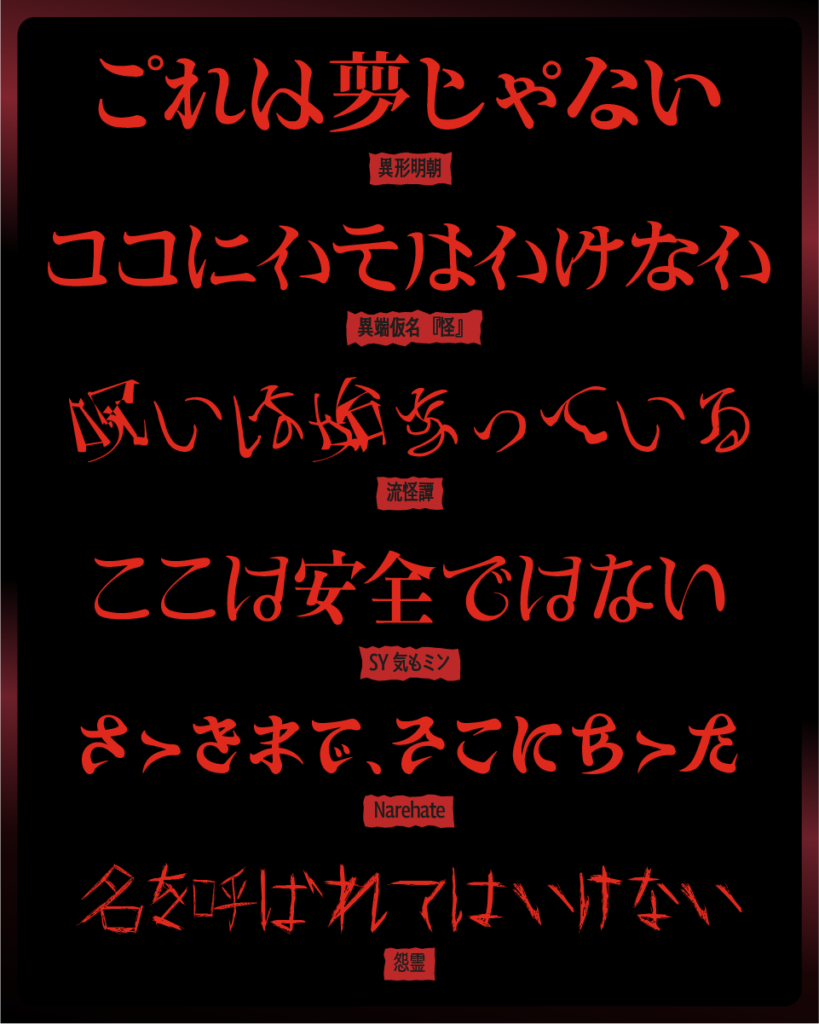
異形明朝
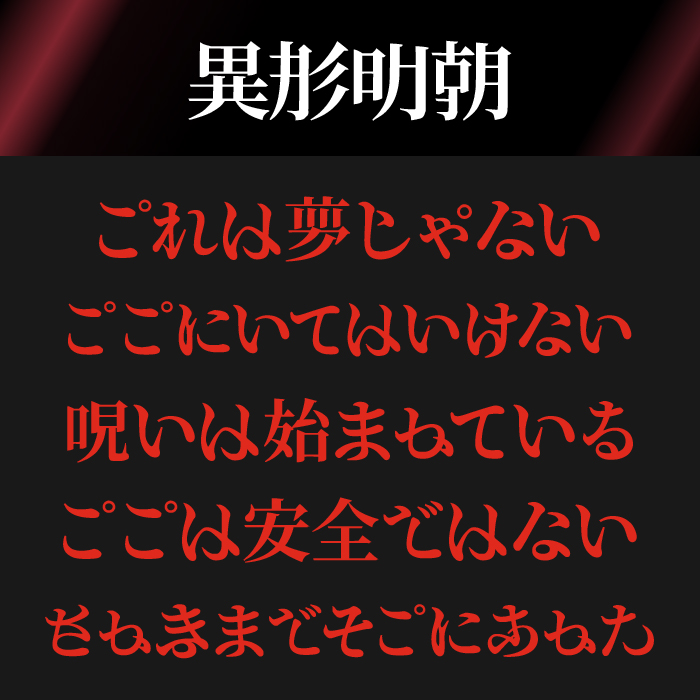
異形明朝は、通常の明朝体のシルエット違い生成AIでチューニングして作られた、異常性と不安感をにじませたフォントです。一見すると美しいが、長く見ているとゾクっとくる異質さを孕んでいます。
怪異の中にある静けさ、不可解な事件、正体不明の存在…といったモチーフとの親和性が高く、ホラー明朝の入り口としても使いやすいフォントです。
流怪譚
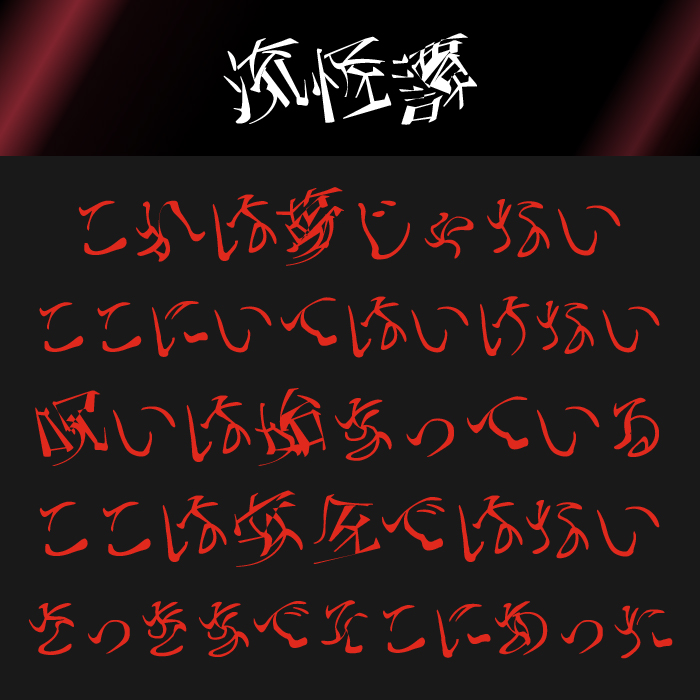
流怨譚は、ぐにゃ〜っと回転しているようなカーブが不気味なフォントです。優雅さを装いながら、明らかにどこかおかしいという違和感があります。
物語性のある怪奇演出、妖しさを含んだ伝奇もの、あるいは「何かが始まりそう」な序章に向いています。視線を引きつける妖艶さと不穏さを併せ持つ稀有なデザインです。
怨霊フォント
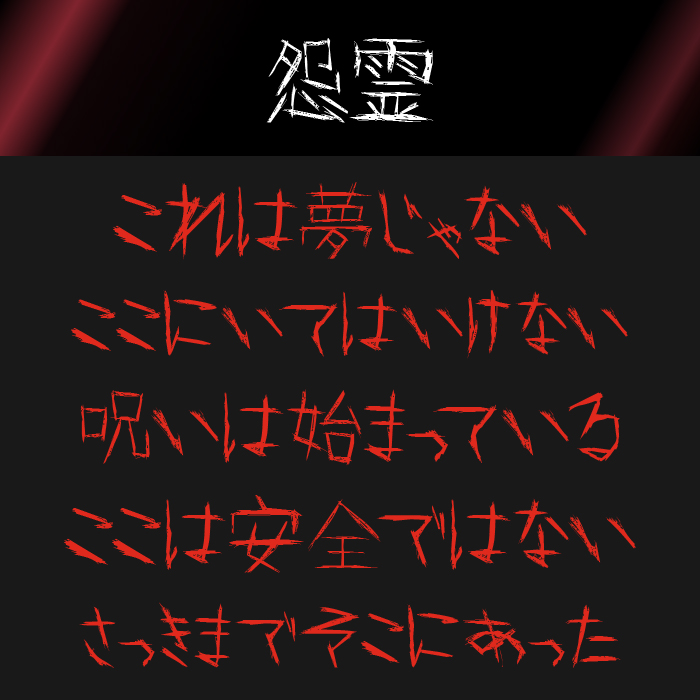
怨霊フォントは、爪で引っ掻いたような筆跡に鋭利さと怒りを宿したような、刺々しい手書き風のデザインです。文字のひとつひとつが叫びのように見え、見ただけで「呪われそう」な緊迫感があります。
恐怖や怨念といったテーマに直結しており、心霊映像やホラー演出のタイトル・字幕などに最適です。過激で破滅的な印象を与えたい場面にぴったりのフォントです。
白舟篆古印
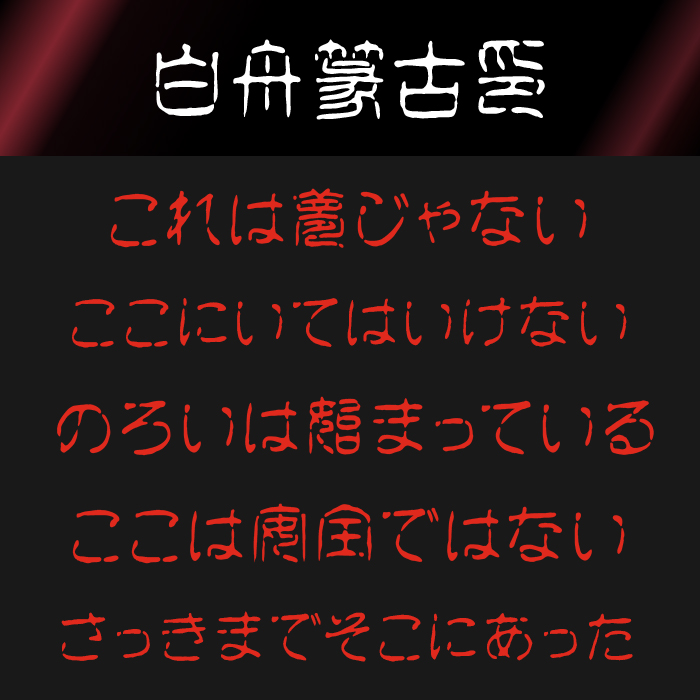
古印体をモチーフとした掠れた筆致が特徴的なおどろおどろしさのある奇怪フォントです。細身ながら芯のある線が、消えかけた怨念や記憶を連想させます。
呪いや怨霊、廃墟、禁忌といったテーマの演出に非常に強く、画面に文字があるだけで物語の温度を一気に冷やすそんなフォントです。
SY気もミン
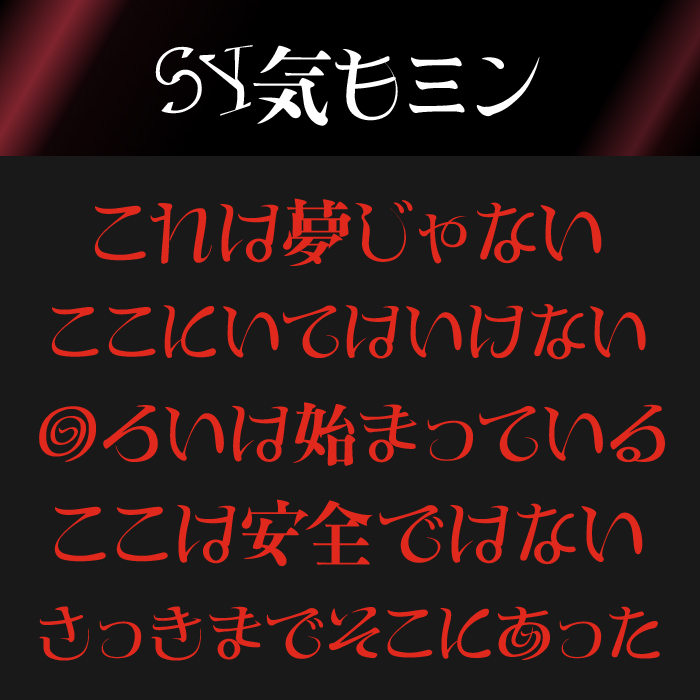
SY気もミンは、ぐにゃとした筆終わりがとっても特徴的で、部分的に奇怪な装飾が施された異形フォントです。曲線と突起が混在し、柔らかさの中に危うさを感じさせます。
いわく付きの手紙、呪文、謎の記号…といった「読めるけど怖い」文字演出にぴったり。
異端仮名『怪』
異端仮名『怪』フォントは、ひらがなとカタカナの融合した異形の文字にゾクゾクとしてしまうユニークなデザインフォントです。
ひらがなとカタカナが組み合わさって作れらていることで「これはなんだろう?」と一見ギョッとしてしまう形ながら、よく見ると読めてしまう不思議なフォントです。
Narehate(なれはて)
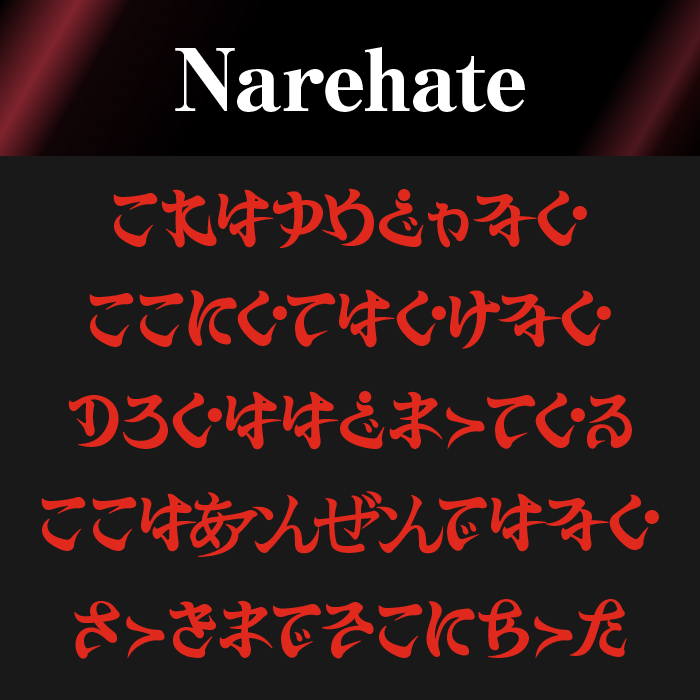
Narehate(なれはて)フォントは、ひらがなの成れの果てのように変形させたデザインフォントです。滑らかながらもどこか常軌を逸したフォルムが、言い知れぬ不安を誘います。
ボトムズ
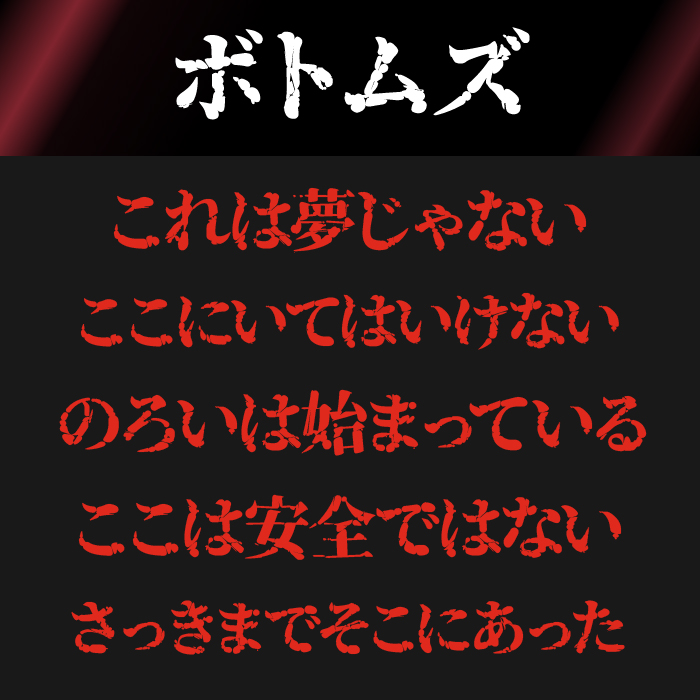
ボトムズフォントは、源ノ明朝をベースとして、沼の底のようなテクスチャを加えて制作されたデザインフォントです。沼底のような奇怪的な強さのあるフォントです。
吐き溜
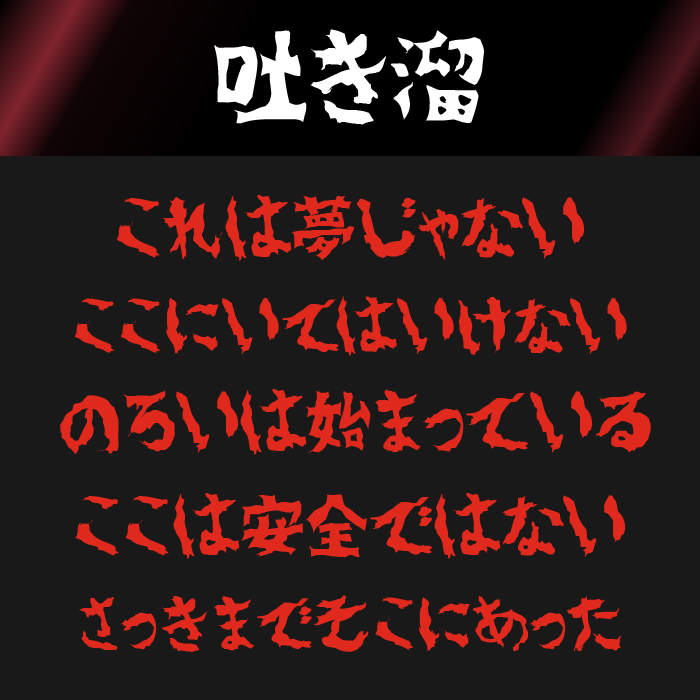
吐き溜フォントは、血が滲んだような鋭利なアウトラインが特徴的なホラーテイストのフォントです。文字のエッジが荒れたようにギザギザしており、不穏でおどろおどろしい空気感を一瞬で演出できるフォントです。
ゆず ペン壊
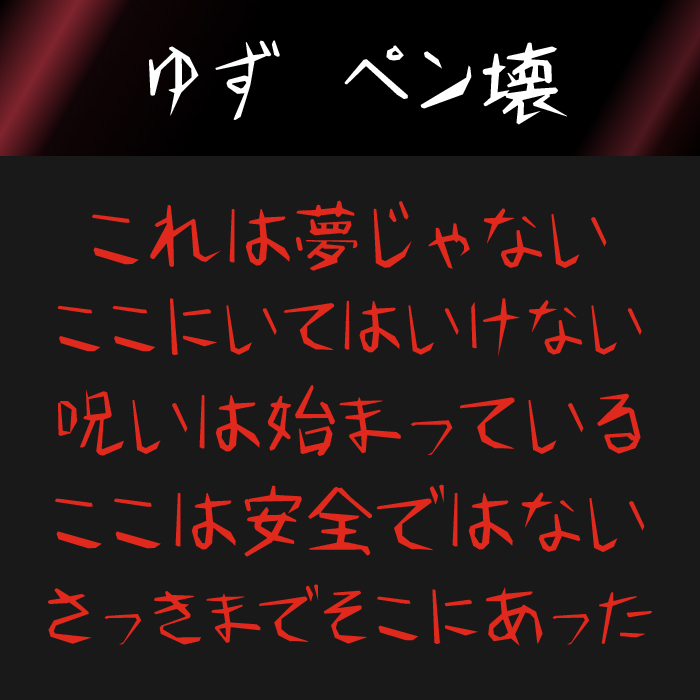
ゆず ペン壊は、呪われている手書きのような破れた紙に無理やり書いたような不安定さがある手書きフォントです。均一でないストロークが、恐怖というより「精神の不安定さ」を強く感じさせてれるそんな手書きフォントです。